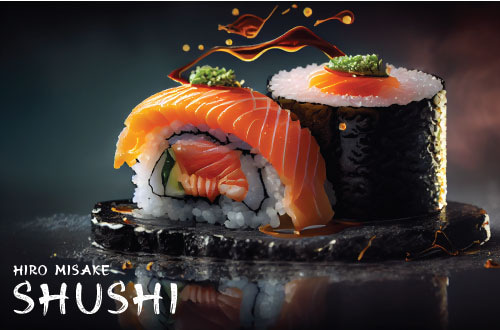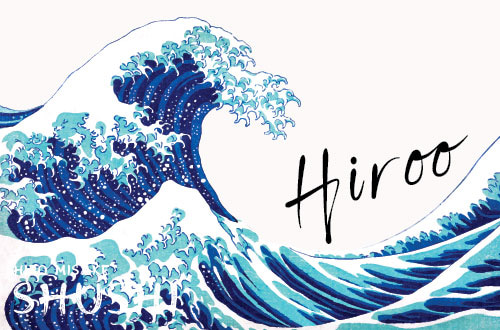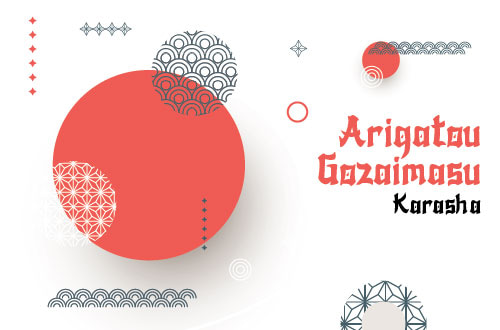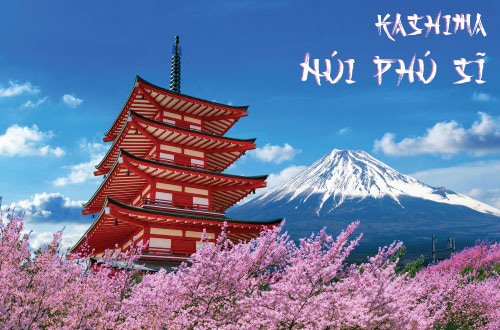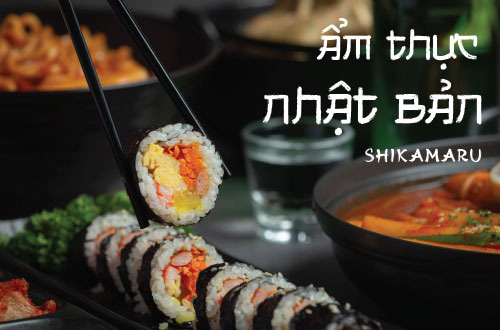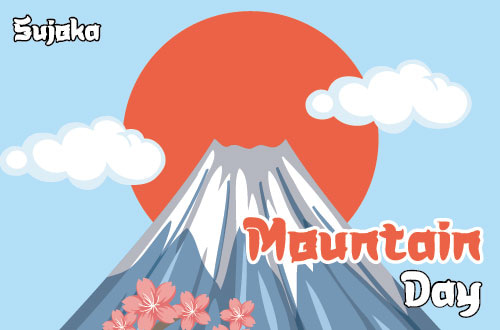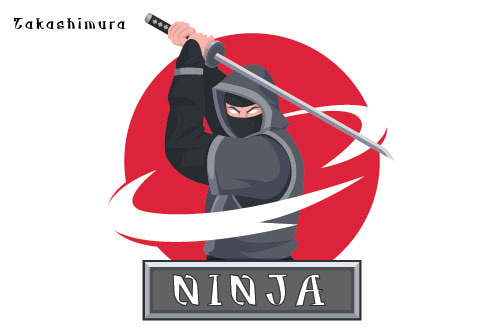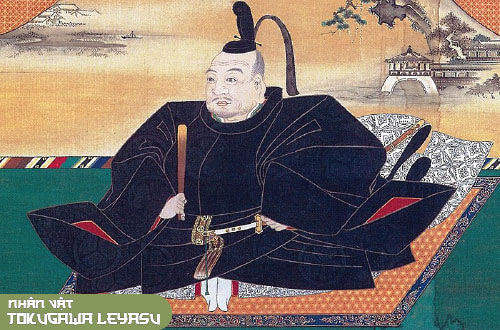
Tổng hợp những font chữ Nhật Bản việt hóa độc đáo và hấp dẫn
Khám phá danh sách tuyển chọn các phông chữ Nhật Bản được việt hóa độc đáo và hấp dẫn trong bài viết này. Dưới đây là những lựa chọn phông chữ kỳ vỹ mà bạn có thể sử dụng trong các thiết kế tiếng Việt, mang đến sự kết hợp tinh tế giữa phong cách Nhật Bản và vẻ độc đáo của ngôn ngữ Việt.
Font chữ Nhật Bản việt hóa là gì?
Để nói một cách đơn giản, bạn có thể hiểu đây là kiểu chữ theo phong cách Nhật Bản nhưng đã được việt hóa để có thể áp dụng trong các thiết kế sử dụng tiếng Việt.
Font Việt hóa Tokugawa
Tokugawa Font Việt hóa
Font chữ Tokugawa: Hòa quyện cảm hứng từ Tokugawa Leyasu
Với nguồn cảm hứng chắc chắn từ Tokugawa Leyasu - một nhân vật vĩ đại trong lịch sử Nhật Bản, phông chữ Tokugawa đã ra đời. Nhân vật này đánh dấu một thời kỳ quan trọng và đầy quyết định trong lịch sử, và phông chữ mang tên ông kế thừa tinh thần đó.
Với những đường nét rất chắc chắn và sắc sảo, phông chữ Tokugawa không chỉ là một dấu ấn độc đáo của văn hóa Nhật Bản mà còn thể hiện sự vĩ đại và quyết đoán của nhân vật mà nó lấy cảm hứng. Đây sẽ là một lựa chọn phông chữ thú vị cho những ai muốn kết nối với tinh thần lịch sử và văn hóa độc đáo của đất nước Mặt trời mọc.
Font Kashima
Kiểu chữ kashima phù hợp cho các loại logo, banner,…
Kashima: Khi Phong cách Nhật Bản Hòa Quyện vào Chữ Cọ
Kashima - một tên gọi truyền cảm hứng - đại diện cho một phông chữ vô cùng tự nhiên và gần gũi. Được tạo ra với tinh thần cách điệu từ văn hóa Nhật Bản, phông chữ này trở nên hoàn hảo cho lĩnh vực thời trang, xây dựng thương hiệu, biểu trượng, tạp chí, trích dẫn, bao bì và quảng cáo.
Bằng cách chứa đựng vẻ đẹp của nét bút lông truyền thống của Nhật Bản, Kashima không chỉ mang lại sự thanh thoát mà còn tạo ra một phong cách độc đáo và tươi mới. Với chữ in hoa, dấu chấm câu, biểu tượng và chữ số, phông chữ này còn thể hiện sự linh hoạt trong việc hỗ trợ đa ngôn ngữ.
Font Takashimura
Font chữ lấy cảm hứng từ thư pháp Nhật Bản
Tách biệt từ nguồn cảm hứng của những bức thư pháp độc đáo và cuốn hút của người Nhật, phông chữ này đã được tạo ra với mục tiêu làm nổi bật trong các thiết kế dưới dạng mang hơi hướng của Nhật Bản, Châu Á và vùng phương Đông. Bên cạnh đó, bộ phông Takashimura đã được việt hóa, đảm bảo khả năng sử dụng linh hoạt trong hầu hết các ứng dụng thiết kế.
Mọi biến thể chữ và ký hiệu trong bộ phông này được tương thích với Unicode (PUA), giúp việc tạo ra hiệu ứng độc đáo trở nên dễ dàng và thuận tiện.
Font Hiroo Script
. Hiroo Script là sự kết hợp tinh tế giữa vẻ đẹp hiện đại và cảm hứng văn hóa Nhật Bản.
Hiroo Script: Khi Hiện Đại Kết Hợp Cùng Cảm Hứng Nhật Bản
Với sự tôn vinh tinh tế từ kiểu chữ Nhật Bản, phông chữ Hiroo Script ra đời như một tác phẩm hiện đại. Mỗi nét chữ được khắc hoạ một cách tỉ mỉ, tạo nên một vẻ ngoài tự nhiên và đẳng cấp cho văn bản của bạn.
Khả năng thích ứng của phông chữ này rất đa dạng, từ nhiếp ảnh, hình mờ, trích dẫn, tiêu đề blog, áp phích, đám cưới, xây dựng thương hiệu, biểu trượng, thời trang, may mặc, thư từ cho đến thư mờ, thiệp mời và văn phòng phẩm. Hiroo Script không chỉ là phông chữ, mà còn là sự kết hợp tinh tế giữa vẻ đẹp hiện đại và cảm hứng văn hóa Nhật Bản.
Font Hiro Misake
Phông chữ này rất thích hợp cho thời trang, xây dựng thương hiệu,...
Hiro Misake là một phông chữ kiểu bút lông mang phong cách Nhật Bản, được tạo ra bằng cách sử dụng bút lông thực sự. Nó trông rất tự nhiên. Phông chữ này rất thích hợp cho thời trang, xây dựng thương hiệu, logo, tạp chí, trích dẫn, bao bì, quảng cáo và nhiều ứng dụng khác, cần phong cách của một cảm giác bút lông Nhật Bản.
Font Shikamaru
Font chữ Shikamaru việt hóa
Shikamaru: Phong cách Nhật Bản Hiện Đại
Shikamaru là một kiểu chữ Nhật Bản, được thiết kế với nét vẽ thô tối giản, bắt nguồn từ vẻ đẹp của chữ Kanji. Với thiết kế chữ in hoa đặc biệt, có sự biến đổi hình dạng giữa chữ in hoa và chữ thường, Shikamaru đơn giản và mang đến một cảm giác chân thực hơn về tinh thần Nhật Bản.
Với tính năng độc đáo của mình, Shikamaru là lựa chọn tuyệt vời cho việc trình bày, đặc biệt trong lĩnh vực thực phẩm Nhật Bản, hàng hóa, biểu trượng, áp phích, trích dẫn ngắn, truyền thông về phim và trò chơi, cũng như trong lĩnh vực thời trang.
Font Sujoka
Phông chữ Sujoka việt hóa
Sujoka: Nét Chữ Vui Tươi và Tinh Nghịch
Sujoka là một phông chữ mang trong mình nét tươi mới và tính nhí nhảnh, tạo điểm nhấn độc đáo cho việc trang trí banner, thực đơn quán ăn, logo thương hiệu, và thậm chí trong việc thiết kế trang phục.
Font Hakubo
Phông chữ Hakubo việt hóa
Hakubo: Độc Đáo từ Cảm Hứng Nhật Bản
Hakubo - một kiểu chữ hiển thị - lấy cảm hứng từ đất nước Nhật Bản. Sức mạnh của nó nằm ở khả năng thể hiện sự độc đáo cho mọi thiết kế! Sự pha trộn này sẽ tạo nên sự tuyệt vời khi được in trên nhãn hiệu áo phông, trên các bản in hay thậm chí trang trí nhà hàng.